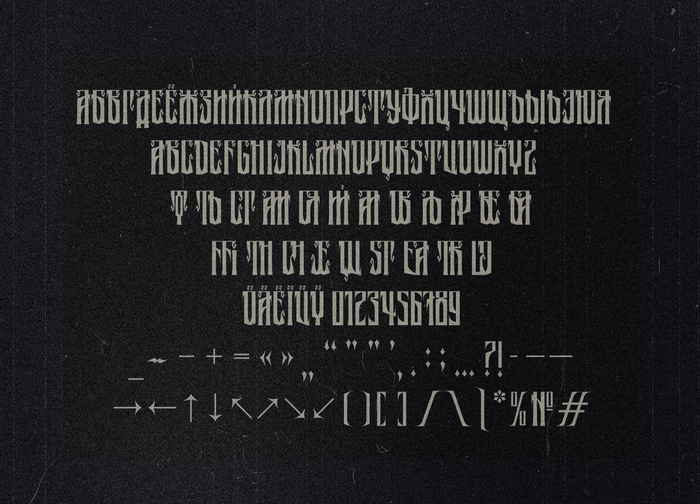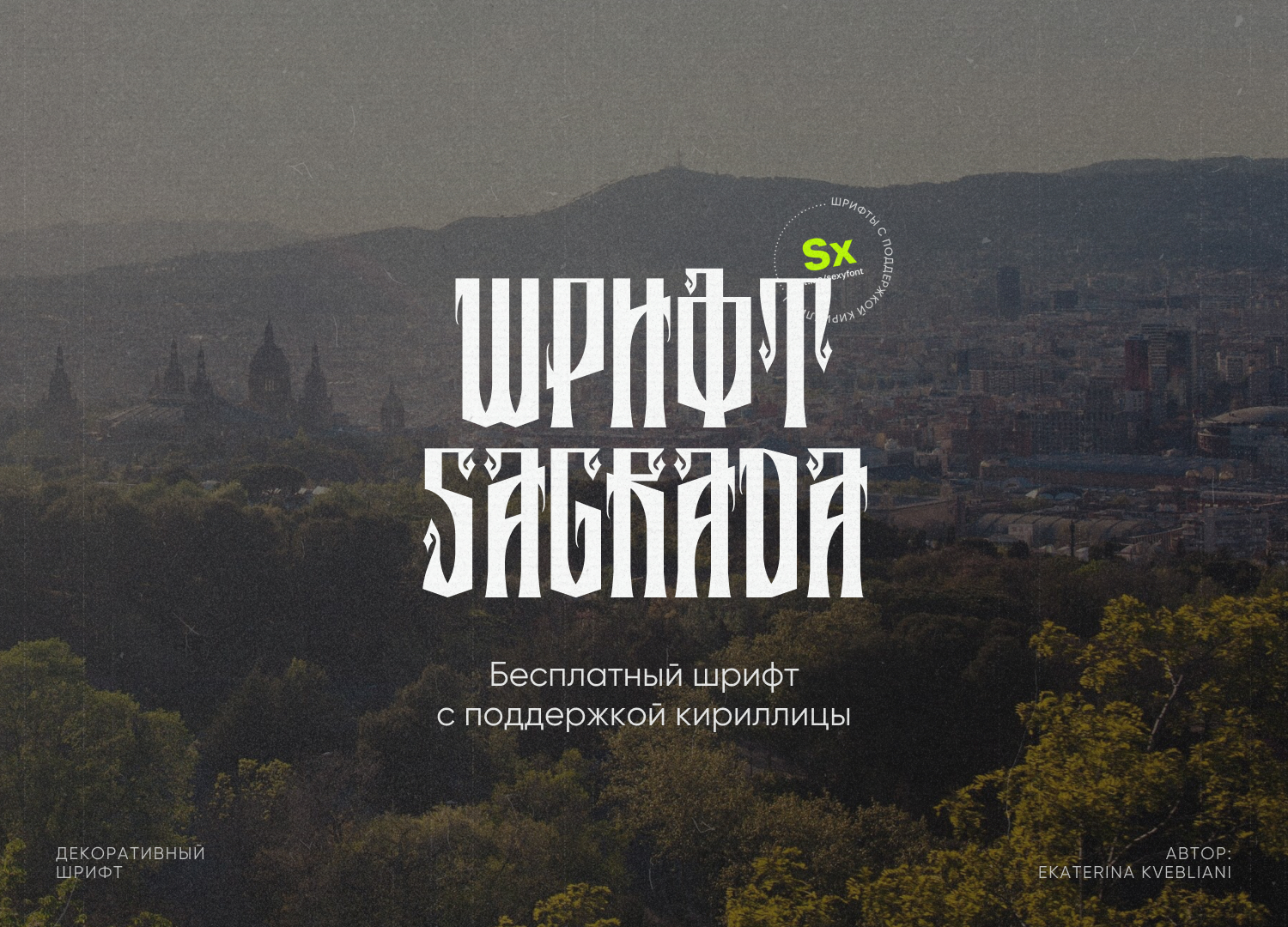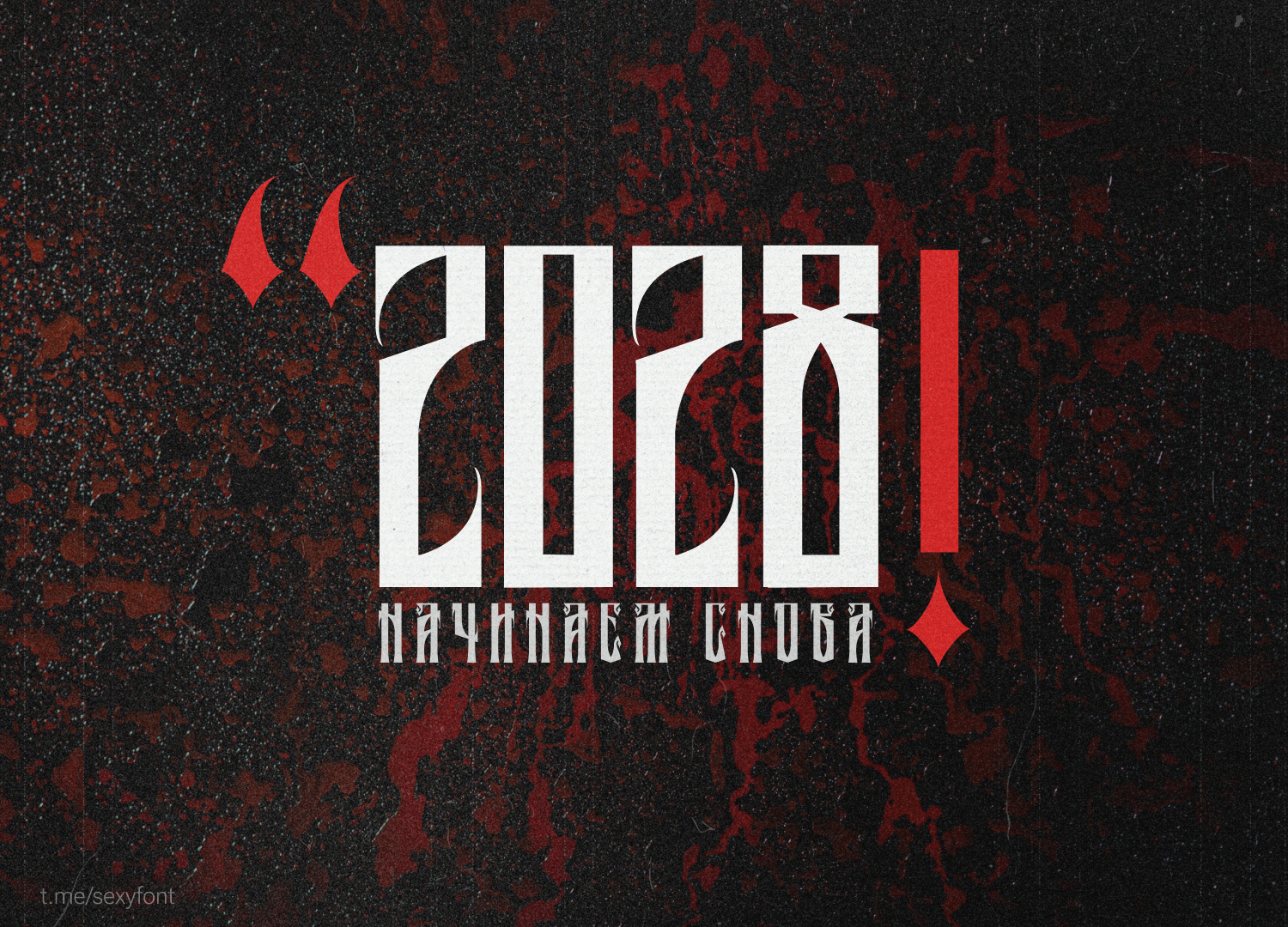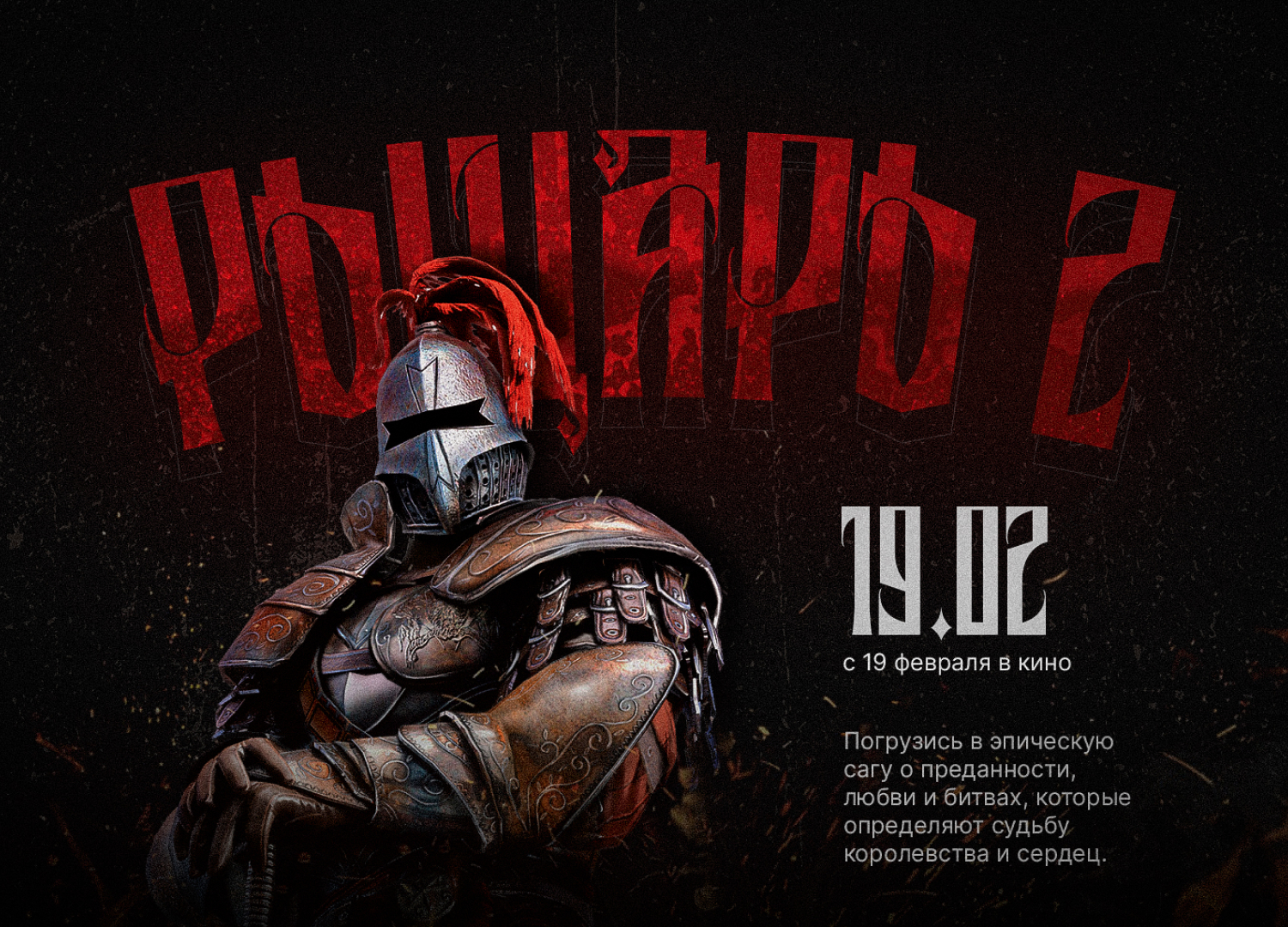
Шрифт Sagrada. Кириллица
Шрифт, вдохновленный готической архитектурой и кириллическими надписями. В каждом письме каждый может найти необычный мистический образ или персонаж.